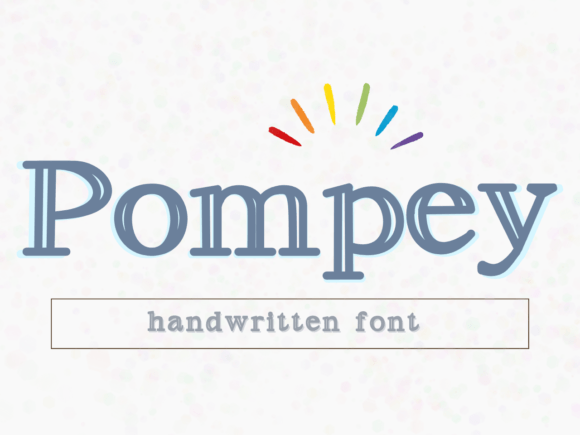
Pompey
Ulasan Lengkap Font Pompey: Pilihan Terbaik untuk Logo, Branding, dan Kutipan
Jika Anda sedang mencari font handwritten yang elegan, timeless, dan penuh karakter, Pompey adalah jawabannya. Dirancang dengan detail yang memukau, setiap huruf pada Pompey memiliki sentuhan unik yang mampu menghidupkan desain Anda dalam sekejap.
Keunggulan Utama Pompey
- Desain Handwritten yang Otentik – Menampilkan goresan alami yang memberi kesan personal dan hangat.
- Cocok untuk Logo & Branding – Karakter kuat tiap huruf membuat identitas visual menjadi lebih menonjol dan mudah diingat.
- Ideal untuk Kutipan & Poster – Gaya tipografi yang elegan memperkuat pesan emosional dalam setiap kalimat.
- Versatilitas Tinggi – Berfungsi dengan baik pada media digital maupun cetak, dari website hingga materi promosi.
Mengapa Pompey Lebih Baik Daripada Font Handwritten Lain?
Berbeda dengan font tulisan tangan yang cenderung generik, Pompey menonjol karena:
- Setiap huruf memiliki detail khusus yang tidak terlihat pada font standar.
- Rasio lebar dan tinggi yang seimbang memastikan keterbacaan tinggi pada ukuran kecil sekaligus tampilan mewah pada ukuran besar.
- Karakteristik “handcrafted” yang tetap konsisten, menjadikannya pilihan aman untuk brand identity.
Tips Menggunakan Pompey untuk Hasil Maksimal
- Padukan dengan Sans‑Serif Minimalis – Misalnya Helvetica atau Montserrat untuk kontras yang modern.
- Gunakan Warna Kontras – Hitam atau warna gelap pada latar terang menonjolkan detail huruf.
- Jangan Over‑kerning – Biarkan spasi alami Pompey bekerja, sehingga tampilan tetap natural.
- Tambahkan Efek Tekstur – Efek kertas atau grain dapat menambah nuansa vintage yang cocok dengan gaya handwritten.
Kesimpulan
Pompey bukan sekadar font handwritten biasa; ia adalah alat kreatif yang dapat mengubah logo, branding, dan kutipan Anda menjadi karya visual yang menawan dan tak terlupakan. Dengan keunikan tiap huruf, kompatibilitas tinggi, dan fleksibilitas desain, Pompey layak menjadi pilihan utama bagi desainer grafis, pemilik merek, dan siapa saja yang ingin memberi sentuhan pribadi pada proyek mereka.